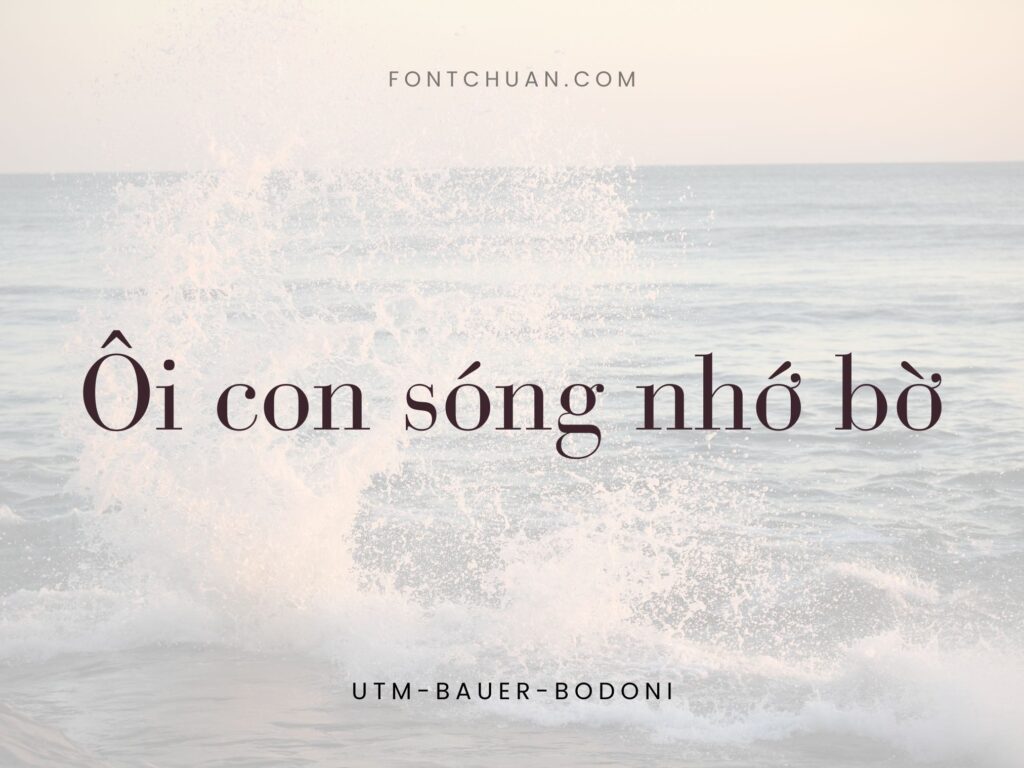
Font UTM Bauer Bodoni Việt Hóa
Việt hóa bởi: Đinh Kiên
UTM Bauer Bodoni là phiên bản Việt hóa của kiểu chữ Bauer Bodoni, một Font Serif nổi bật do Heinrich Jost thiết kế vào năm 1926, dựa trên nguyên bản Bodoni nổi tiếng của Giambattista Bodoni từ thế kỷ 18. Font mang vẻ đẹp cổ điển với độ tương phản cao giữa nét thanh và nét đậm, tạo nên sự sang trọng và trang nhã. Phiên bản Việt hóa được thực hiện bởi Đinh Kiên, hỗ trợ đầy đủ tiếng Việt cùng hơn 100 ngôn ngữ khác. Đây là một trong những font đã được thành viên Font Chuẩn sưu tầm và chọn lọc để phục vụ các dự án thiết kế yêu cầu sự chuyên nghiệp và tinh tế.
UTM Bauer Bodoni sở hữu các nét chữ dứt khoát, chân chữ không bo tròn (unbracketed serif), và tỷ lệ ký tự chuẩn mực, thích hợp trong các thiết kế cần thể hiện tính học thuật hoặc cao cấp. Font rất phù hợp với thiết kế sách, bìa tạp chí, tiêu đề trang trọng, thiệp mời hoặc các ấn phẩm thương hiệu. Những ngành nghề như quảng cáo, giáo dục, bất động sản và công nghệ có thể tận dụng font này để tạo cảm giác chuyên nghiệp, cổ điển và đáng tin cậy.